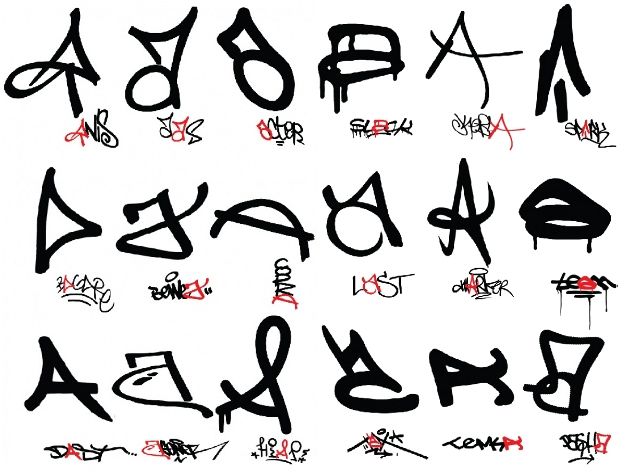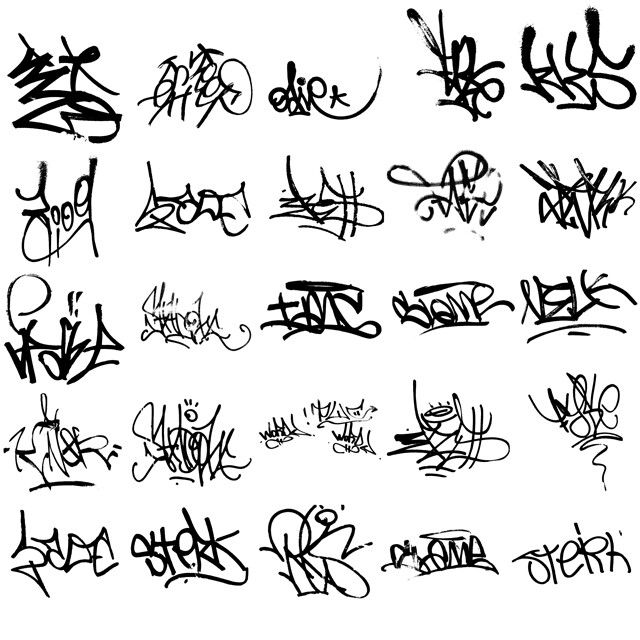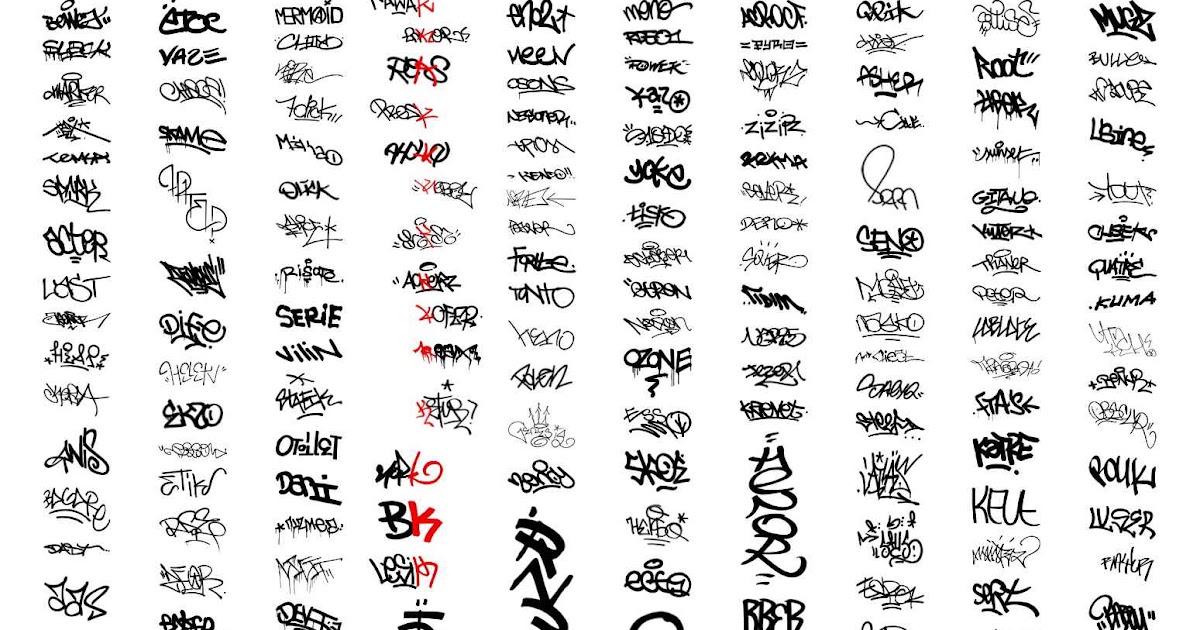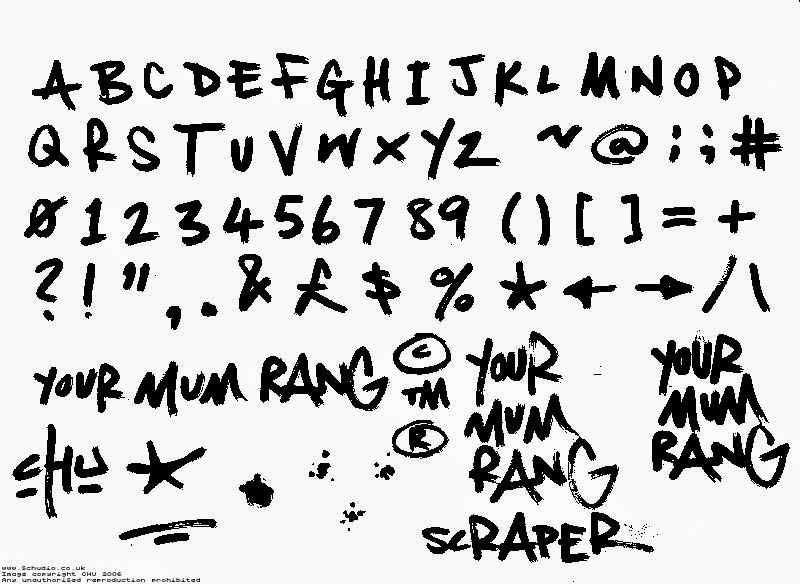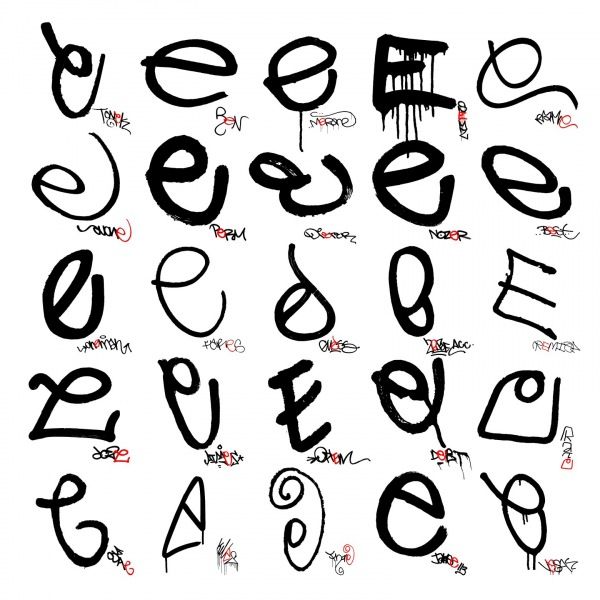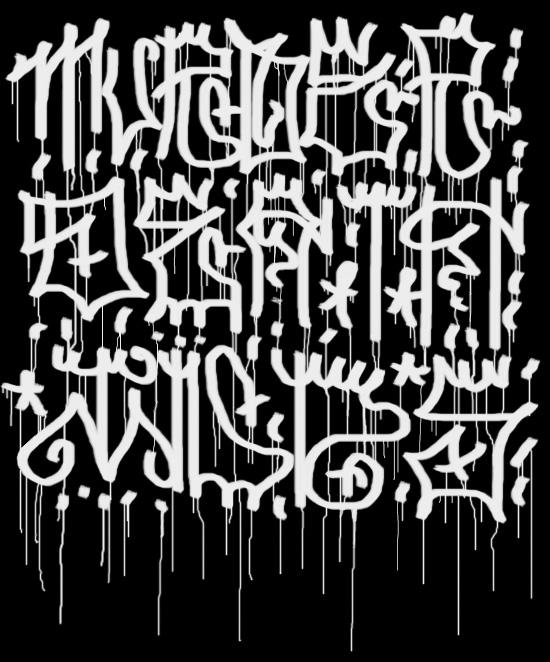
2003 — graffitifonts.
net выходит в интернетГотовясь к выпуску первой официальной коллекции компакт-дисков, литейный завод Graffiti Fonts® запускает специальный сайт. Начиная с 13 сентября 2003 г., когда домен .com занят, коллекция предварительно просматривается в домене .net перед выпуском. Хотя литейный завод был запущен в 1999 году, и их первые несколько шрифтов были впервые опубликованы на fulltimeartists.com, запуск этого сайта ознаменовал собой первый широкомасштабный выпуск коллекции.